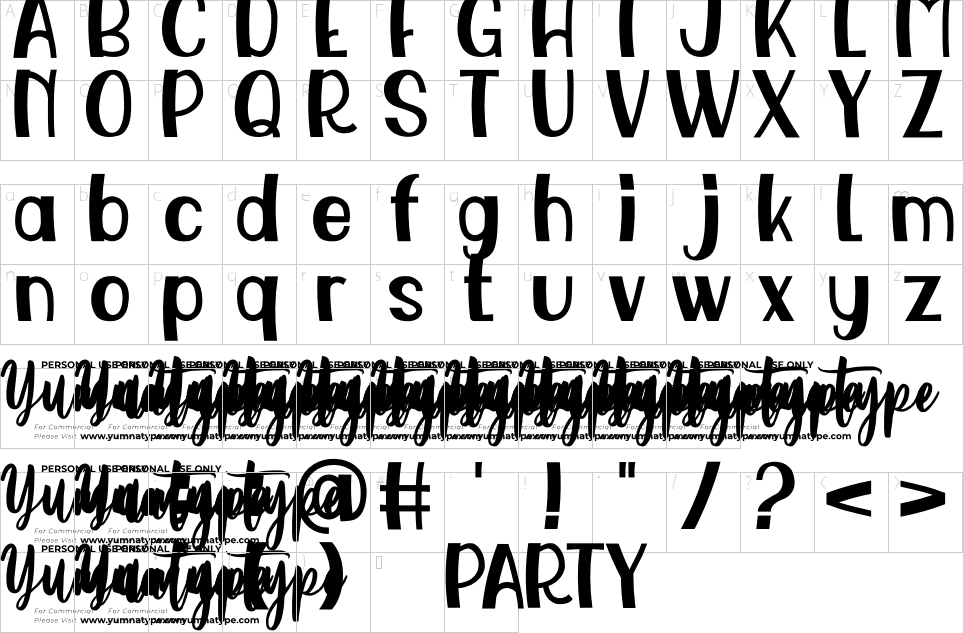
Awesome Paerty Display Font – Download Grátis
Descubra a fonte Awesome Paerty Display, projetada para criar ambientes festivos e animados. Esta fonte é perfeita para personalizar seus documentos, apresentações ou qualquer projeto que exija um toque de diversão e estilo. Awesome Paerty Display foi projetada pela Yumna Type, e já foi baixada 5.055 vezes. Descubra por que os criativos e os designers estão adorando essa fonte única e divertida. Instale-a em seu computador Windows ou Mac e transforme o modo como você expressa os eventos notáveis na sua vida. Sem dúvida, essa é uma fonte que enriquecerá seus projetos. Download a fonte Awesome Paerty Display hoje e faça sua impressão sair das páginas.